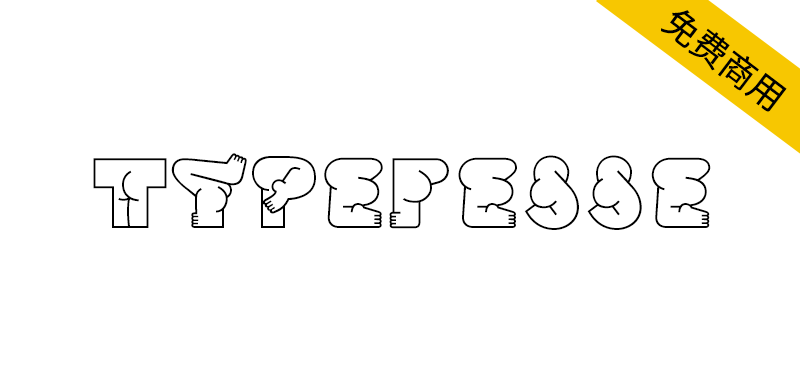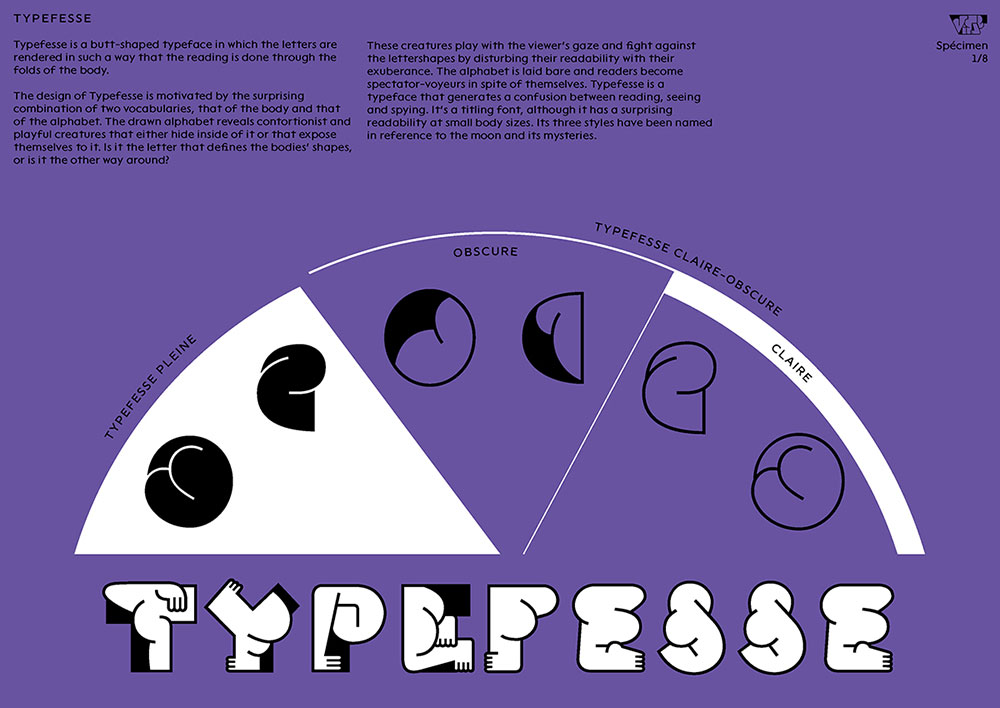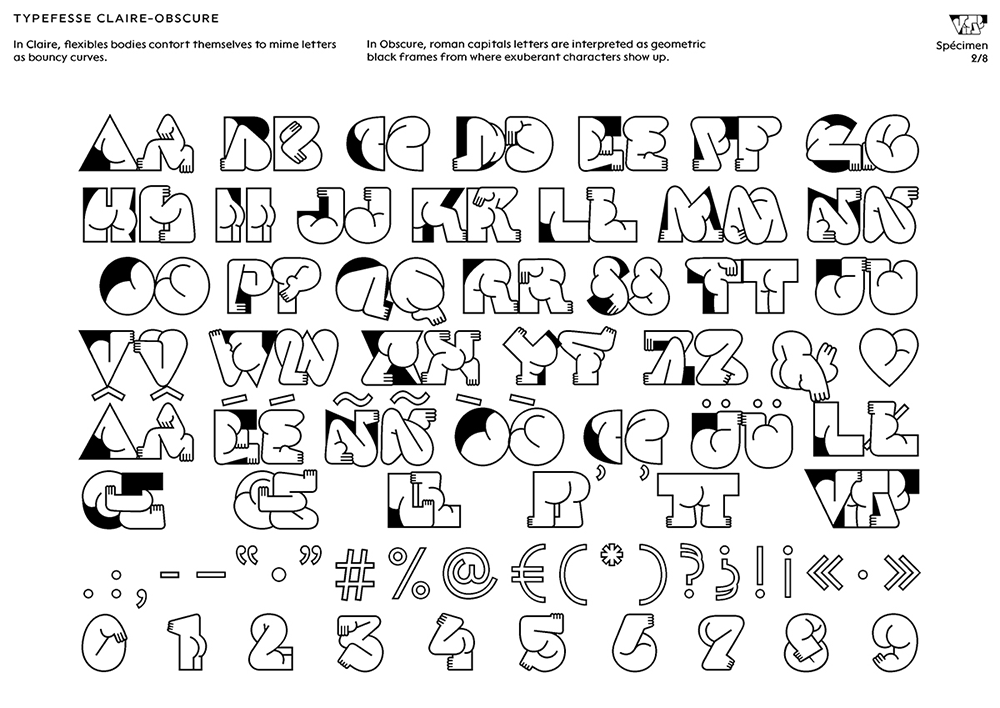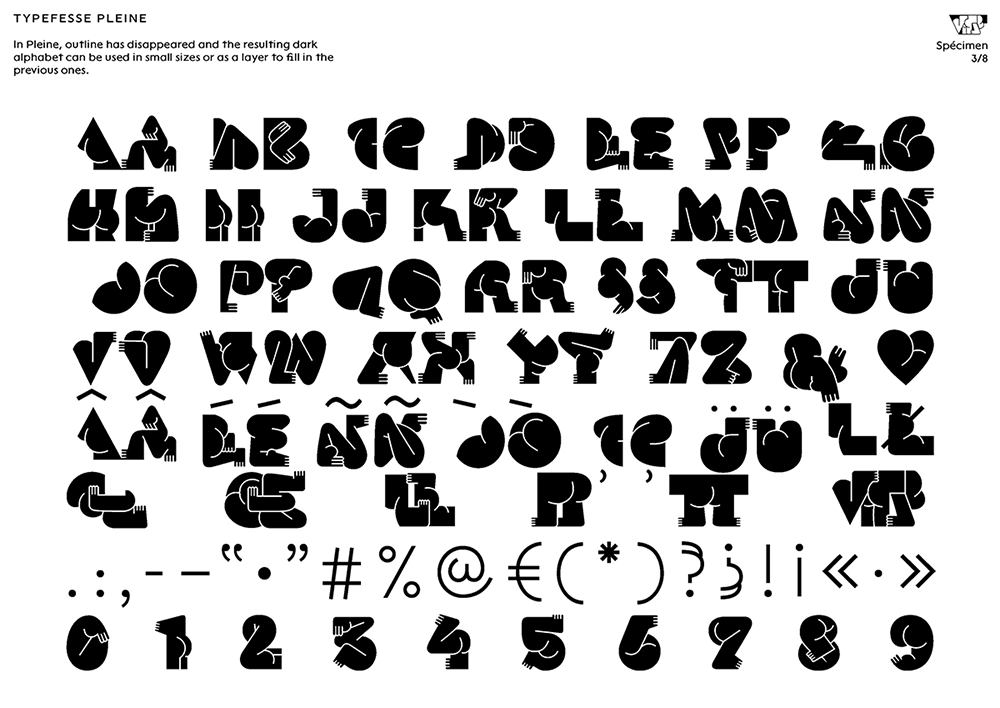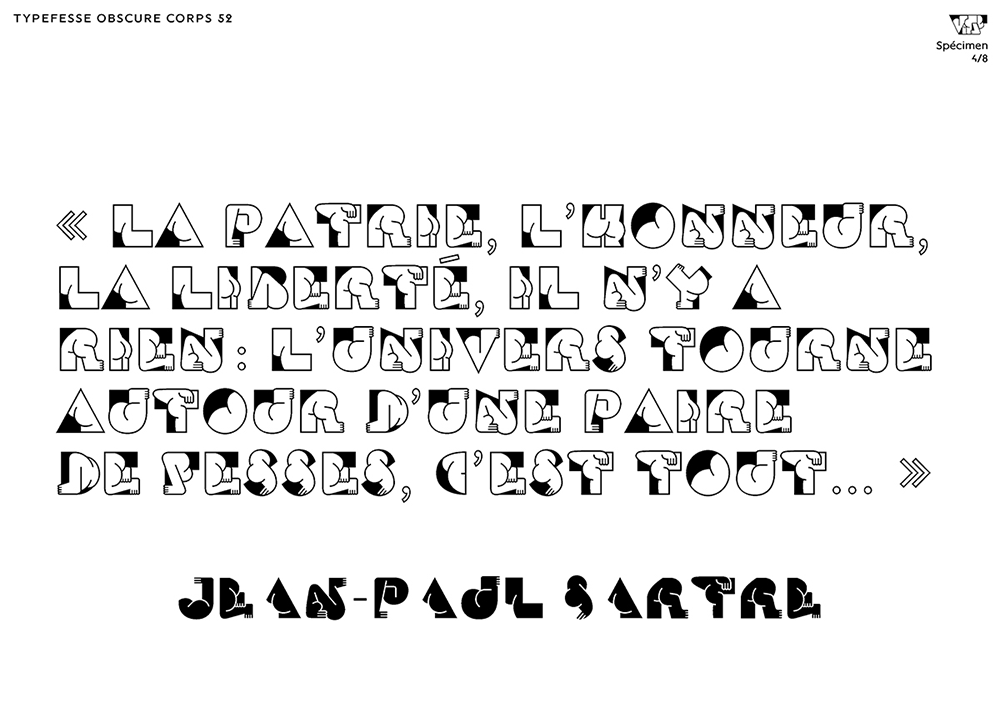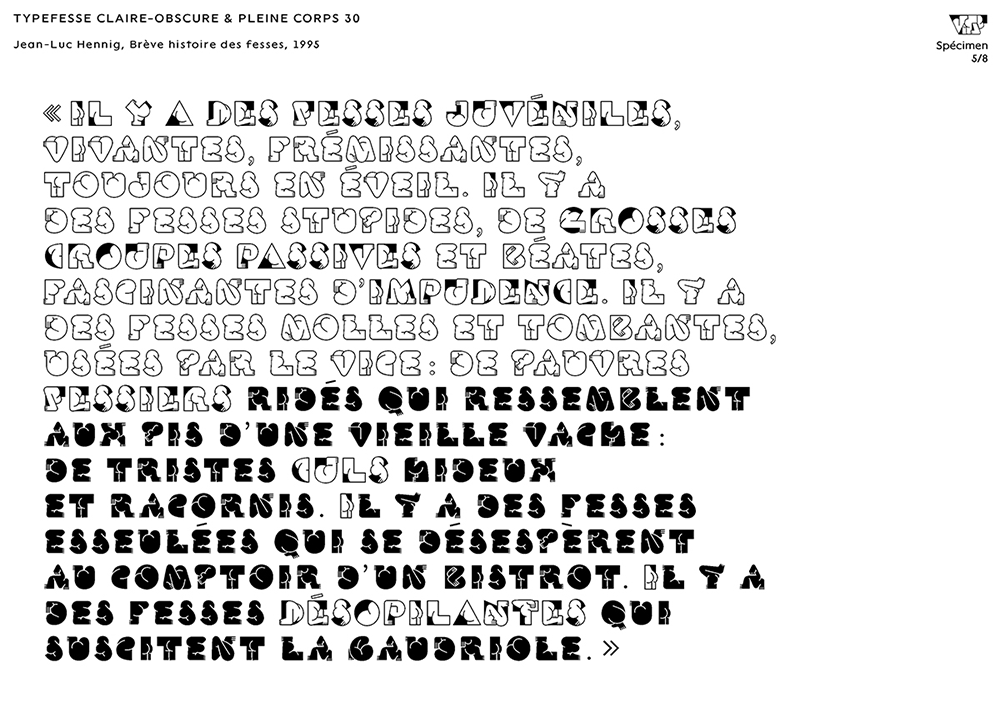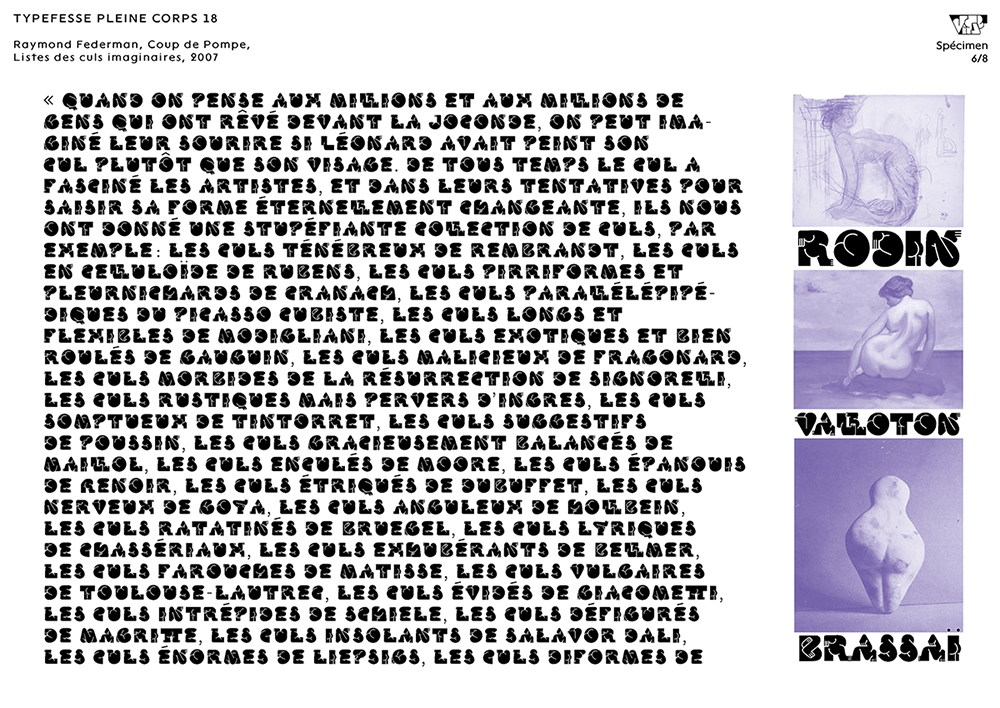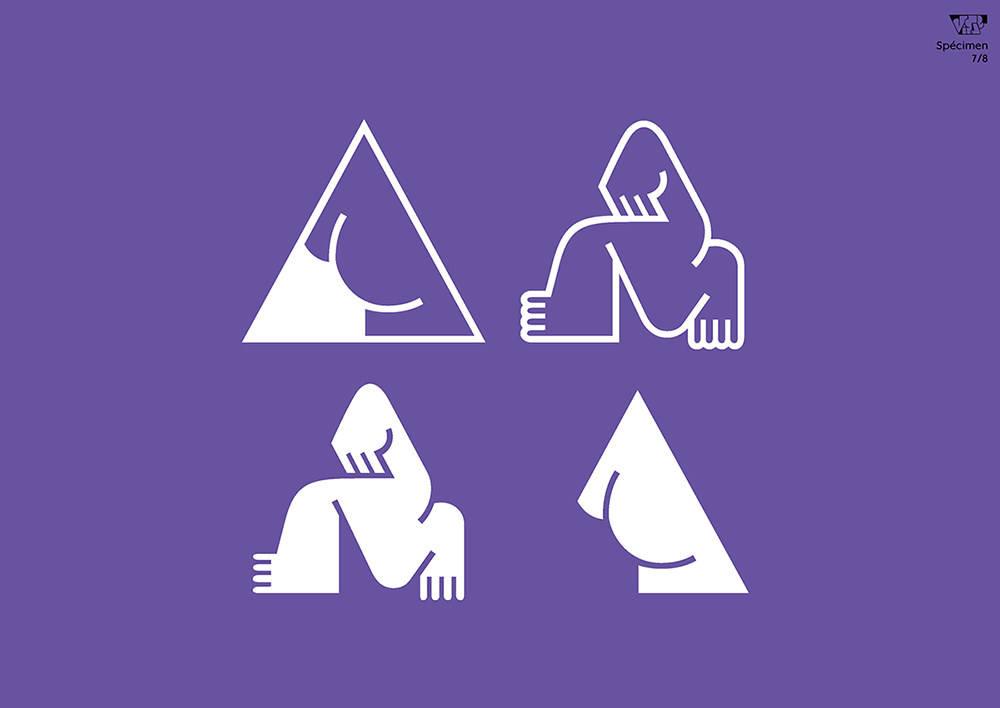
【Typefesse】一种有趣的屁股形状的英文字体
当字母与身体形态的界限被打破,会诞生怎样颠覆认知的字体?Typefesse用臀部褶皱重构26个字母,让阅读变成一场充满窥视感的视觉游戏!这款免费商用字体通过三种月球命名风格制造奇妙冲突:扭曲蜷缩的Claire、核心留白的Pleine、锁孔式图形的Obscure——它们既挑战传统可读性边界,又在小字号下保持意外清晰。文字不再是冰冷符号,而是扭动身躯与你对视的顽皮生物,模糊了阅读、观察与窥探的界限。设计师用身体曲线解构字母骨架,你准备好解锁这场字体与身体的暧昧对话了吗?
【Typefesse】一种有趣的屁股形状的英文字体
Typefesse是一种有趣的屁股形状的字体,其中字母的呈现方式是通过身体的褶皱进行展示。Typefesse的设计灵感来自于两个词汇的惊人组合,即身体和字母。绘制的字母显示了扭曲和顽皮的生物,它们要么躲在里面,要么暴露在里面。是字母定义了身体的形状,还是反过来?这些生物与观众的目光嬉戏,并通过用它们的活力扰乱它们的可读性来对抗字母形状。字母被暴露出来,读者会不由自主地成为观众的窥探者。Typefese是一种在阅读、观察和监视之间产生混淆的字体。这是一种标题字体,尽管它在小字体下具有令人惊讶的可读性。它的三种风格是根据月球及其神秘性命名的:
Claire —— 这是最敏捷的风格,也是最扭曲的。身体被迫扭曲或卷曲,以适应字母。当它们组合在一起形成一个单词时,它们似乎相互依偎,使字母符号的相邻性更加亲密。
Pleine —— 这种风格表示字母的中心。它允许在较小的体型下具有最大的可读性,并且可以用作Claire和Obscure风格之上的附加层。
Obscure —— 这是最图形化的风格,也是最像插图的。字母表被表示为各种锁孔,读者通过这些锁孔可以发现字母的背面。这些字母被视为游戏空间。
它们以2种字体文件排序:Typefesse Claire Obscure,大写字母为Obscure;小写字母为Claire;Typefesse Pleine,轮廓已被删除。
Typefesse is a playful butt-shaped typeface in which the letters are rendered in such a way that the reading is done through the folds of the body.The design of Typefesse is motivated by the surprising combination of two vocabularies, that of the body and that of the alphabet. The drawn alphabet reveals contortionist and playful creatures that either hide inside of it or that expose themselves to it. Is it the letter that defines the bodies' shapes, or is it the other way around? These creatures play with the viewer's gaze and fight against the lettershapes by disturbing their readability with their exuberance. The alphabet is laid bare and readers become spectator-voyeurs in spite of themselves. Typefesse is a typeface that generates a confusion between reading, seeing and spying. It's a titling font, although it has a surprising readability at small body sizes. Its three styles have been named in reference to the moon and its mysteries :
Claire — This is the most agile style, and the most contorted. The bodies are forced to twist or curl up in order to fit inside the letters. When they're set together to form a word, they seem to snuggle against each other and they make the adjacency of alphabetic signs more intimate.
Pleine — This style designates the heart of the letters. It allows the greatest readability at small body sizes and can be used as an additional layer on top of the Claire and Obscure styles.
Obscure — This is the most graphical style and the most illustration-like. The alphabet is represented as an assortment of lock holess through which the reader discovers the backside of letters. The letters are treated like spaces of play.
They are ordered in 2 font-files: Typefesse Claire-Obscure where capitals are Obscure whereas lower cases are Claire and Typefesse Pleine where outlines have been removed.